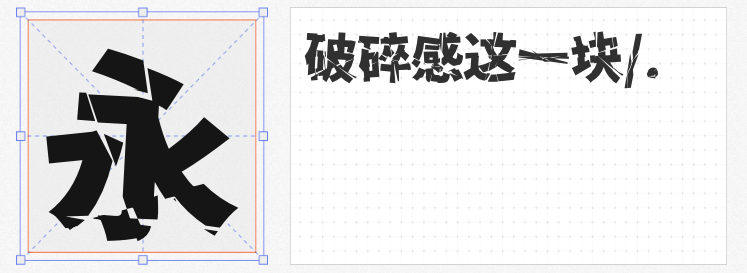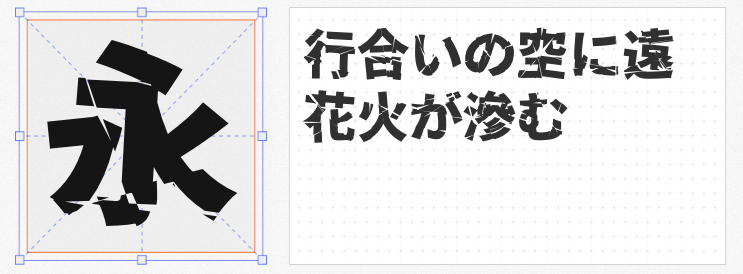
在视觉竞争白热化的今天,一款自带特效的创意字体往往能成为设计的点睛之笔。本文精选四款免费商用且极具视觉冲击力的字体,它们或切割扭曲、或故障破碎,让文字跳出平面,成为吸引眼球的利器。
香萃零度黑
源自日文字体【零ゴシック】的开源项目,香萃零度黑以近7000个简化字构建出极具侵略性的视觉语言。笔画通过扭曲与分裂设计,远观如流动的金属曲线,近看则呈现精密的直线切割效果。设计师巧妙保留部分日本汉字字形,同时微调标点位置以适应中文排版习惯,使其在海报标题、品牌标识等场景中极具辨识度,尤其适合科技、潮牌等领域的视觉表达。
破碎零号字 (零ゴシック)
基于思源黑体改造的破碎零号字,以8000+字符覆盖中文全场景需求。其核心特色在于笔画中的断裂处理,通过不规则的缺口与错位,营造出一种动态的破碎感。这种“破坏性重构”既保留了文字的可读性,又赋予标题与Logo强烈的视觉张力,是朋克摇滚、电竞游戏等亚文化设计的绝佳选择。
猫啃网故障宋 / 猫啃网故障黑
猫啃网故障宋继承思源宋体CN的庞大字库,通过程序自动生成故障特效,虽偶有字形瑕疵,但整体呈现的信号干扰、像素失真效果,完美复刻了数字时代的故障美学。而猫啃网故障黑则更进一步,借鉴日本瀞之故障黑体,将思源黑体转化为充满霓虹光晕与数据噪点的赛博字体。两款字体均自带科幻滤镜,是网页设计、海报标题、短视频字幕的吸睛神器。